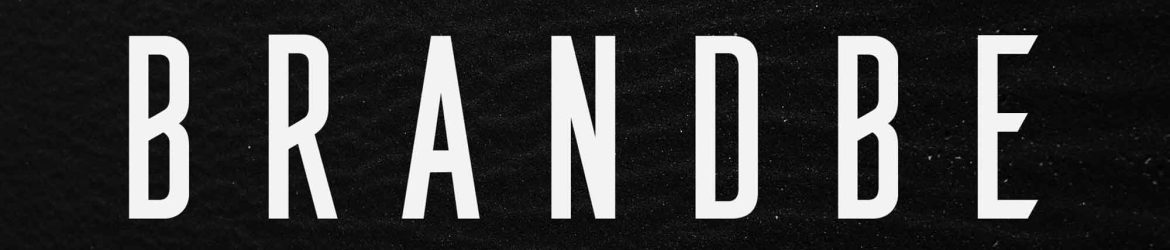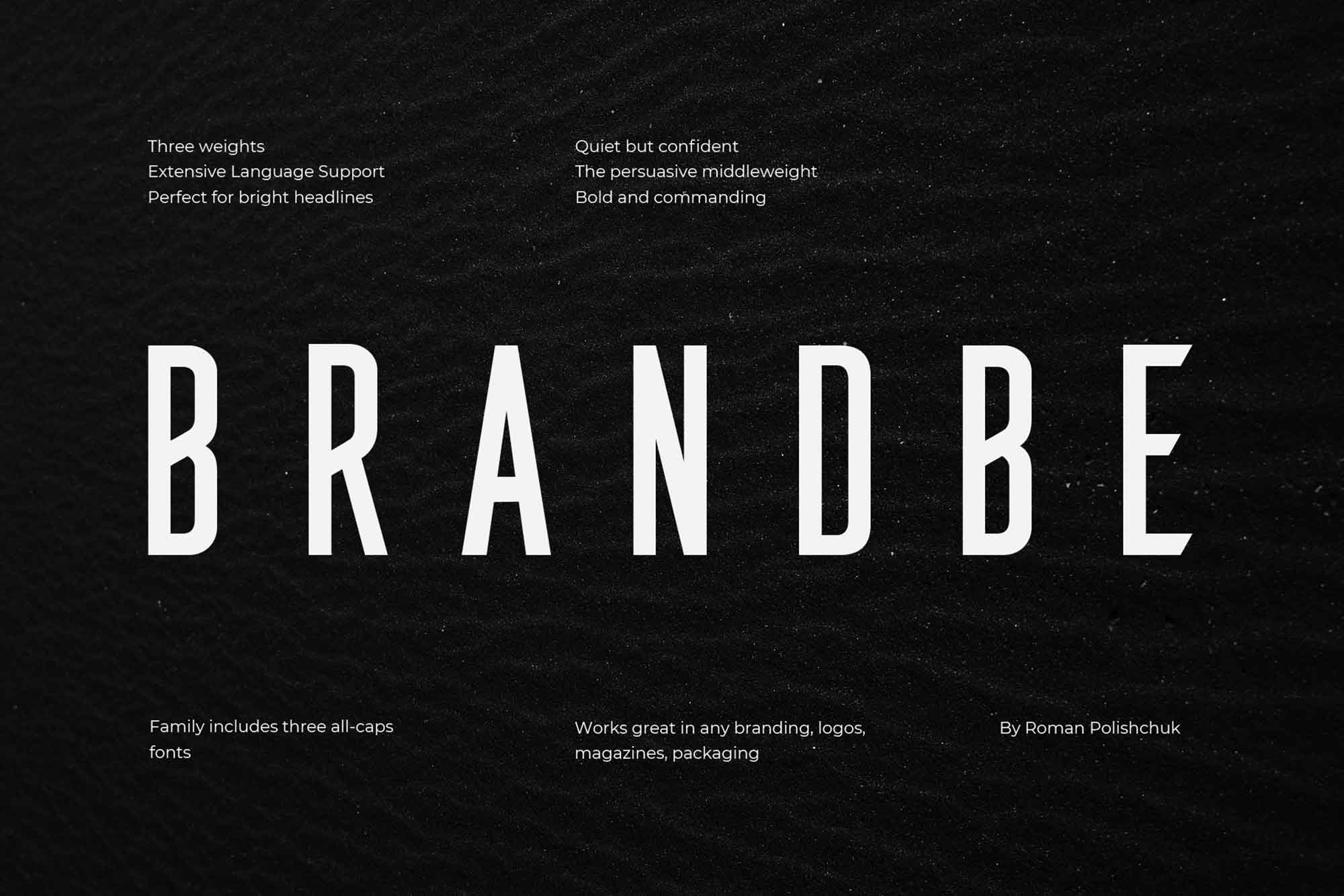
Brandbe Sans Serif Font
A Brandbe Sans Serif Font é uma fonte serif que traz uma configuração vertical compacta, perfeitamente adaptada para aplicações em grandes headlines. Ela foi criada por Roman Polishchuk e é todo em caixa alta, apresentando três pesos: leve, médio e grosso. Esta é a fonte ideal para destaque, especialmente para headlines e títulos de capa de revistas, sites ou materiais de marketing. A Brandbe é um recurso gratuito de uso pessoal, oferecendo uma variedade de opções de peso e design único, sem custos adicionais. Ela é uma ótima escolha para quem busca estilizar seu conteúdo de maneira elegante e eficaz, sem precisar gastar dinheiro.